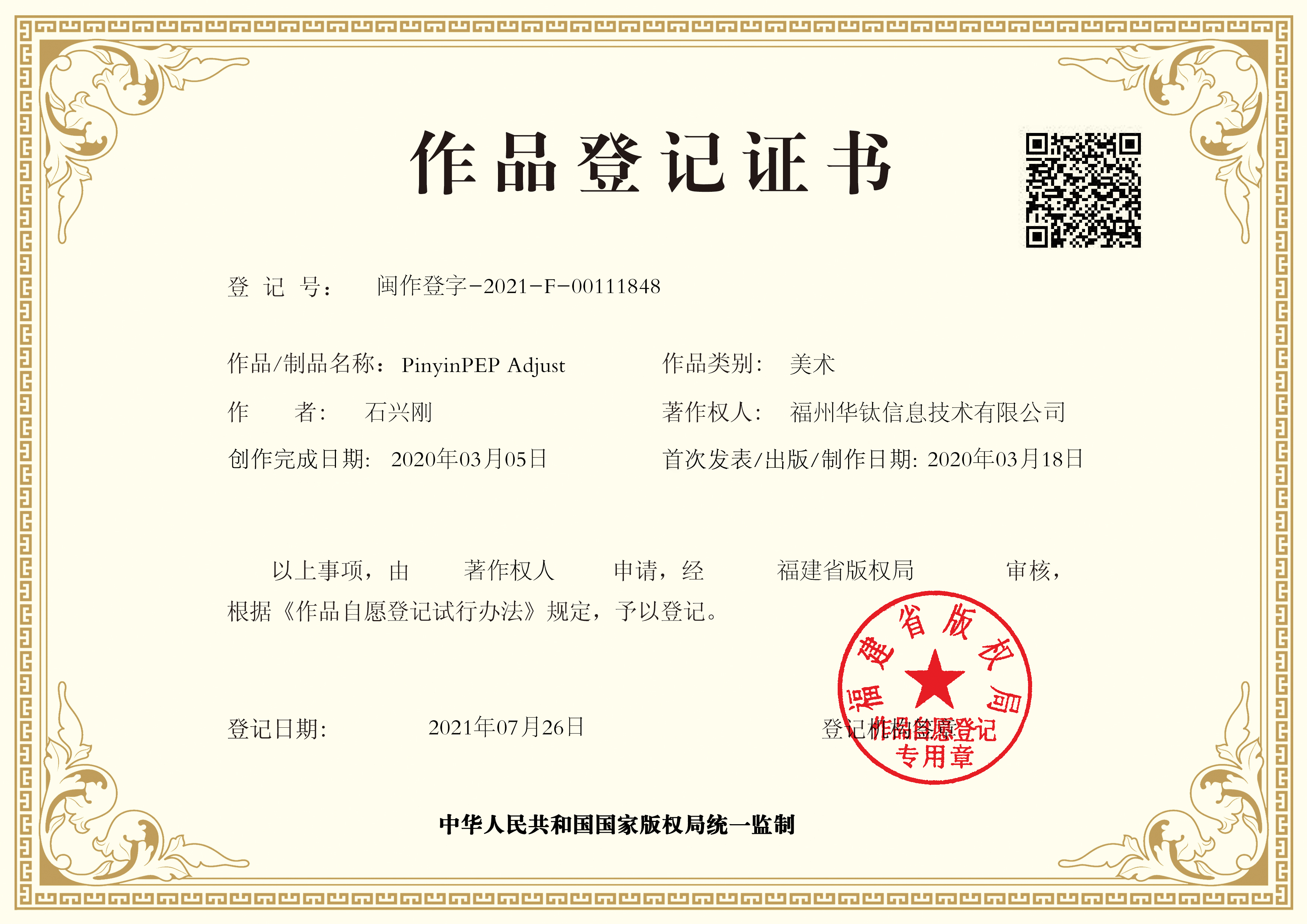
Pinyin PEP Adjust Pinyin PEP Adjust
Pinyin PEP Adjust Pinyin PEP Four Adjust
Pinyin PEP Adjust Pinyin PEP Four Four Adjust
Pinyin PEP Adjust Pinyin PEP Four Three Adjust
Pinyin PEP Adjust Pinyin PEP Four Two Adjust
Pinyin PEP Adjust系列字体是由福州华钛信息技术有限公司创作的拼音字体,该字体广泛应用于教辅印刷、字帖制作等场景。